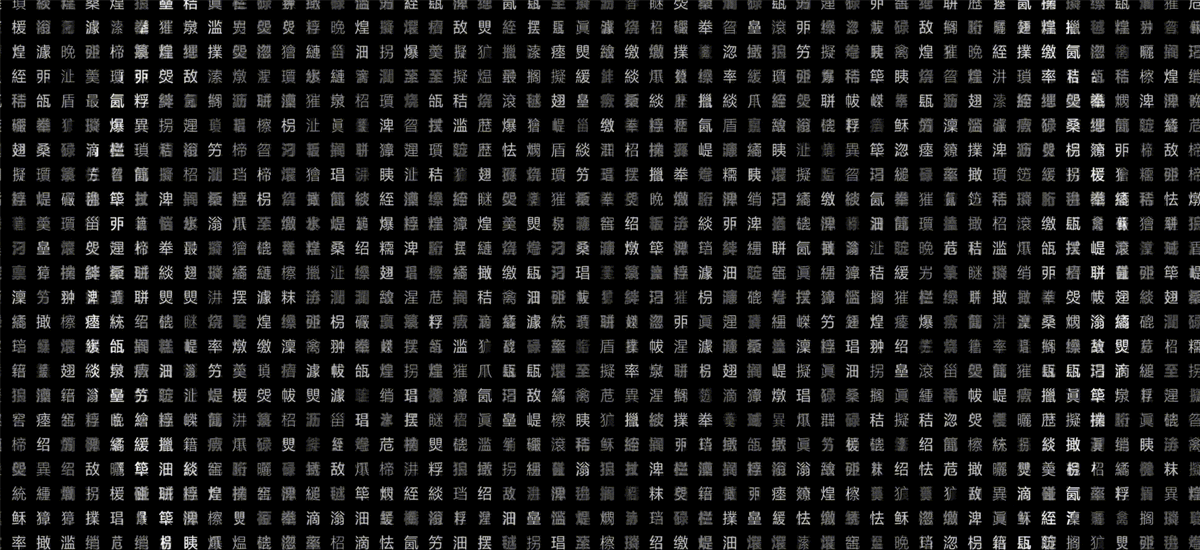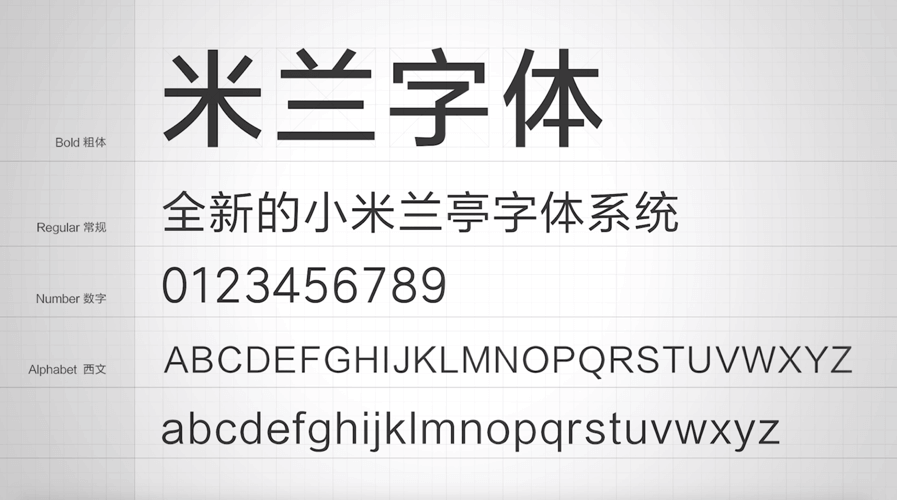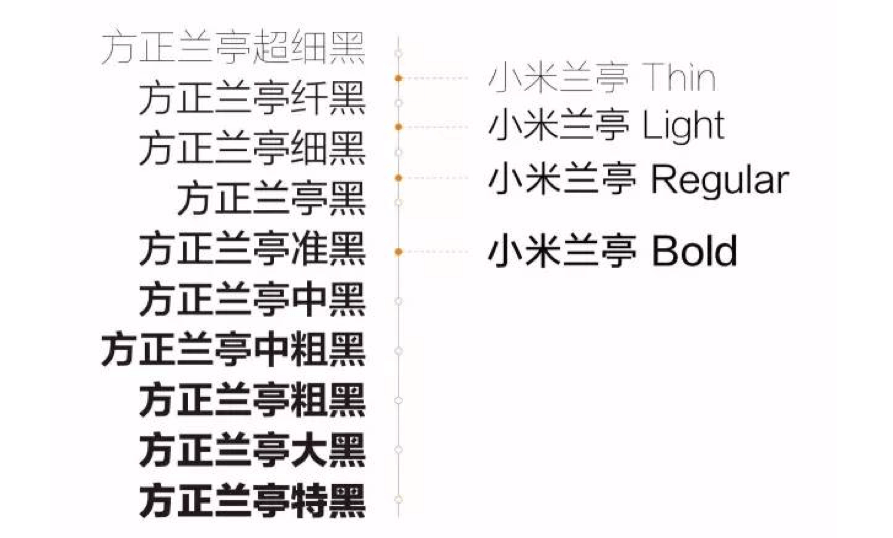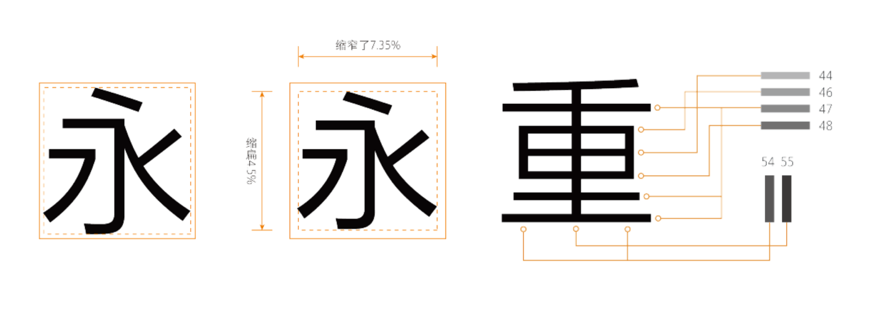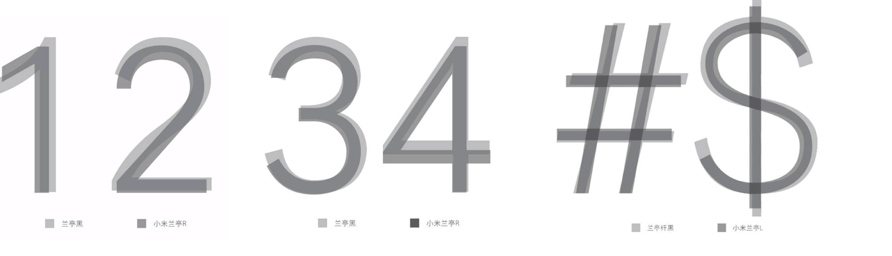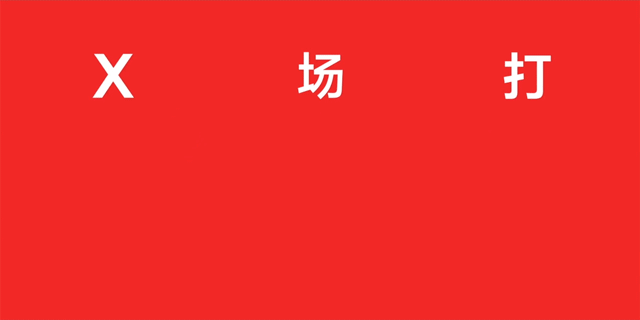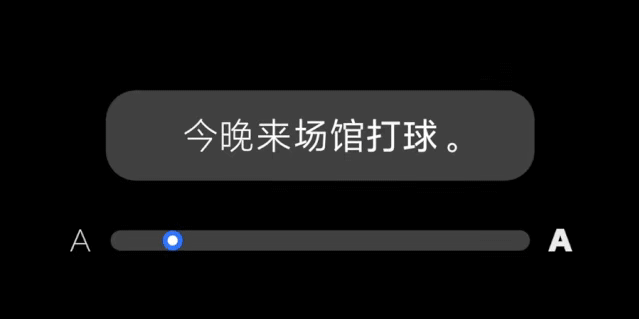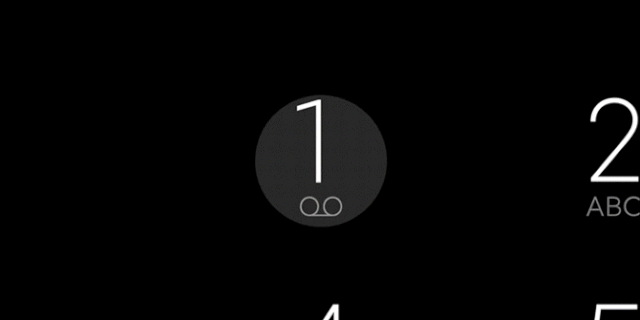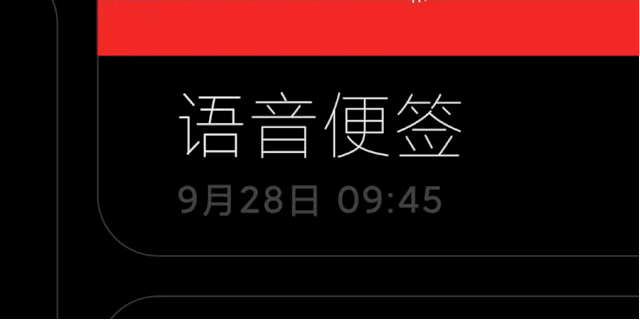
小米兰亭黑//小米兰亭Pro
多年来,小米公司一直在使用方正兰亭黑字体作为其MIUI系统的原生字体。 早在一年多前开发MIUI7系统时,为了更好的满足移动互联网的展示和阅读特性,提升用户体验,小米公司就提出了在方正兰亭黑的基础上定制字体的需求。 作为合作方和服务方,方正字库安排专业团队,全力为小米公司进行设计开发。 做字体是一个浩瀚的工程,经过和小米团队一起历时18个月的精心打磨,最终完成了在MIUI8系统中完美呈现的“小米兰亭”字体。
小米兰亭共设计了4档不同的字重:Regular(简称“R”)、Bold(简称“B”)、Light(简称“L”)和Thin(简称“T”)。
小米兰亭Regular尝试了多组数据方案,小米方面反复测试MIUI使用效果,从2015年5月初到6月底,历经两个月才确定了适用于当时MIUI的字体修改参数。
小米兰亭Regular字重介于兰亭黑与兰亭细黑之间。
小米兰亭Bold在regular的基础上加粗调整,字重大致相当于兰亭准黑,字面及长宽比保持与regular协调一致。
小米兰亭Light字重介于兰亭细黑和兰亭纤黑之间。
小米兰亭Thin基本与兰亭超细黑一致,而符号部分和一些笔画少的字略有加粗。
为配合新一代MIUI的设计,提供更好的阅读体验,方正字库应小米要求,精心调整了汉字的字面、笔画的粗细,对非压缩字库和压缩字库都进行了精细设计。
字间距
数字符号
小米兰亭Pro
2019年9月24日下午,小米公司在北京召开了“小米5G新品发布会”,推出了包括小米9 Pro、小米MIX Alpha在内的一系列新品,全新的MIUI 11系统也在发布会上正式亮相。MIUI 11系统以“声色双全、效率革新”为宗旨,围绕 “设计”、“办公”、“出行”等多方面进行全面升级。
作为中文系统字体定制的先驱,此次MIUI 11系统不仅带来了全新的小米兰亭Pro,还重磅推出了全球首家动态字体系统,希望为用户提供极致的阅读体验。
在MIUI 11系统中,用户可以通过“设置-显示-字体大小与粗细”的操作进入字体模块,拖动相应滑块即可改变手机界面用字的字体大小和字重粗细。MIUI动态字体支持文字粗细无级调节,每个人都可找到适合自己的字重。
智能加粗还会根据内容层级和重要性予以文字不同程度加粗,使阅读体验更为极致。搭载了动态字体系统的MIUI 11,在交互细节上也做了大量优化和提升。
在系统字体越来越受手机厂商重视的当下,此次小米推出的MIUI 动态字体系统无疑是业界的一次重大突破,也是手机系统搭载可变字体的一次有益尝试。据了解,MIUI 动态字体系统获得了2019红点奖。